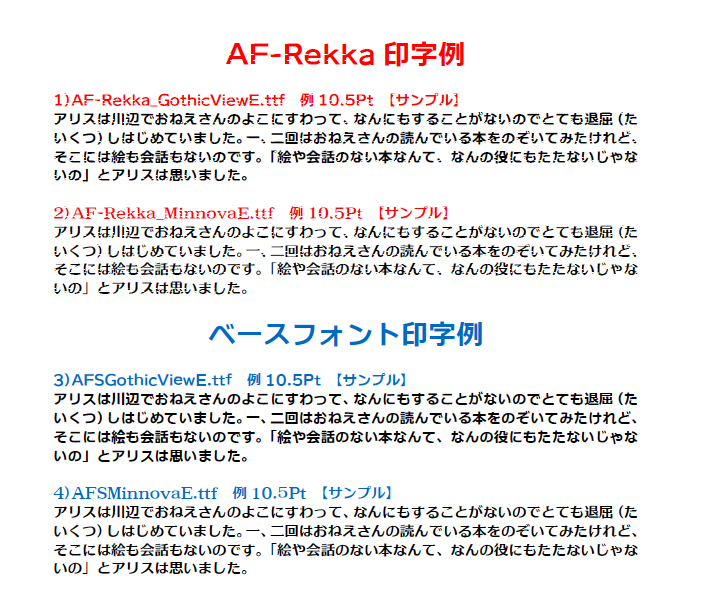
CP932 JISX0213 1990 字形(例:辻は一点しんにょう)
AF-Rekka_GothicViewE
AF-Rekka_MinnovaE
AFSGothicViewE
AFSMinnovaE
※プレビューフォントは「AF-Rekka_GothicViewE」です。
FAX送信された印字のようなドット抜け等の劣化を模したデザインフォント。劣化イメージを誇張したいときに最適です。
AF-Rekka明朝ゴシック2書体、元となったベースフォント2書体、合計4書体セットのデザイン向けフォントです。ベースフォントは販売中のAFSゴシックビューEとAFSミンノバE、劣化フォントと共に同梱しました。